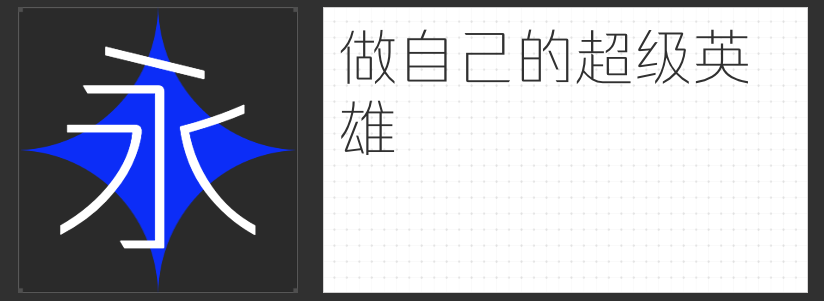
匠心字韵:四款内嵌字体赋能设计美学新表达
在视觉传达设计中,字体不仅是信息载体,更是情感与文化的重要媒介。四款专为内嵌场景打造的字体——励字仿宋简繁、励字书宋简繁、励字超级勇士简特细、励字美黑简,以独特的设计语言与工艺美学,为品牌视觉、包装设计、数字出版等领域注入专业级表现力。
一、励字仿宋简繁
基于宋版书刻字工艺的仿宋字体,以"楷书骨架+宋体笔意"的融合设计,构建出笔画粗细均匀、字形端庄秀丽的视觉体系。其横竖笔画的黄金比例与撇捺的弧度控制,完美复现了古籍排印的呼吸感。在茶文化品牌包装中,该字体以"永"字为例,横细竖粗的对比度精准控制在1:2.3,既保留传统书法的韵律美,又适配现代印刷工艺。
二、励字书宋简繁
这款正宗老宋体以"横轻竖重"为设计基准,通过0.3mm的笔画粗细调节,在保持传统宋体肃穆感的同时,提升小字号阅读的舒适度。其字形结构严格遵循黄金分割比例,中宫紧凑而不局促,特别适合法律文书、学术期刊等严肃场景。在金融类PPT设计中,标题使用该字体的"励"字,竖画末端0.5mm的三角衬线,能有效强化权威感与专业度。
三、励字超级勇士简 特细
作为黑体家族的革新之作,特细字重(0.8pt)设计突破传统黑体的机械感。通过笔画起收处的45°斜切处理,既保持黑体的现代感,又赋予字体流动的韵律。在科技产品宣传册中,该字体以"永"字呈现0.02mm的笔画交叉补偿技术,确保特细字重下的文字可辨识度。中宫匀称的设计理念,使其在信息密集型排版中仍能保持呼吸感。
四、励字美黑简
这款创新字体将黑体的几何结构与宋体的衬线美学进行基因重组。通过0.6mm的笔画粗细过渡控制,在"励"字的"力"部形成独特的视觉张力。其12°的字体倾斜角设计,既保留宋体的典雅气质,又注入黑体的动感基因。在时尚杂志内页排版中,该字体通过0.3mm的墨迹扩散模拟技术,实现屏幕显示与印刷效果的统一。
四款字体通过精密的笔画控制、科学的结构设计与多元的美学融合,构建起从传统到现代、从严肃到灵动的完整设计语言体系。其专业级的工艺标准与场景适配能力,正在重塑高端设计领域的字体应用范式。